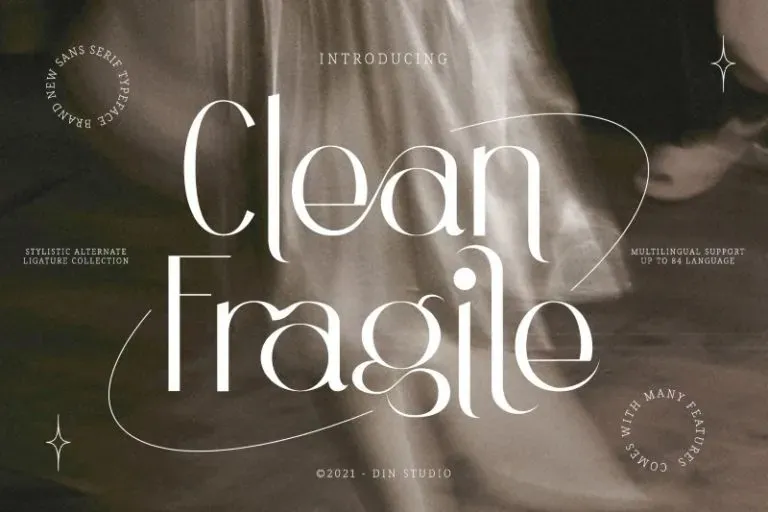
A Clean Fragile Font é uma elegante fonta serif retro, projetada para manter uma vibe moderna e sofisticada. Criada pelo designer Din Studio, esta fonte se destaca por sua facilidade de uso no design gráfico e web, fornecendo um toque sofisticado em qualquer projeto. Ideal para expressar sentimentos aventureiros e elegantemente diretos, cada traço e curva foi cuidadosamente criado para transmitir felicidade e elegância. É perfeita para apresentações, designs gráficos e ilustrações web. A Clean Fragile Font é uma escolha ideal tanto para iniciantes quanto para profissionais, oferecendo um toque único e personalizado a qualquer projeto.